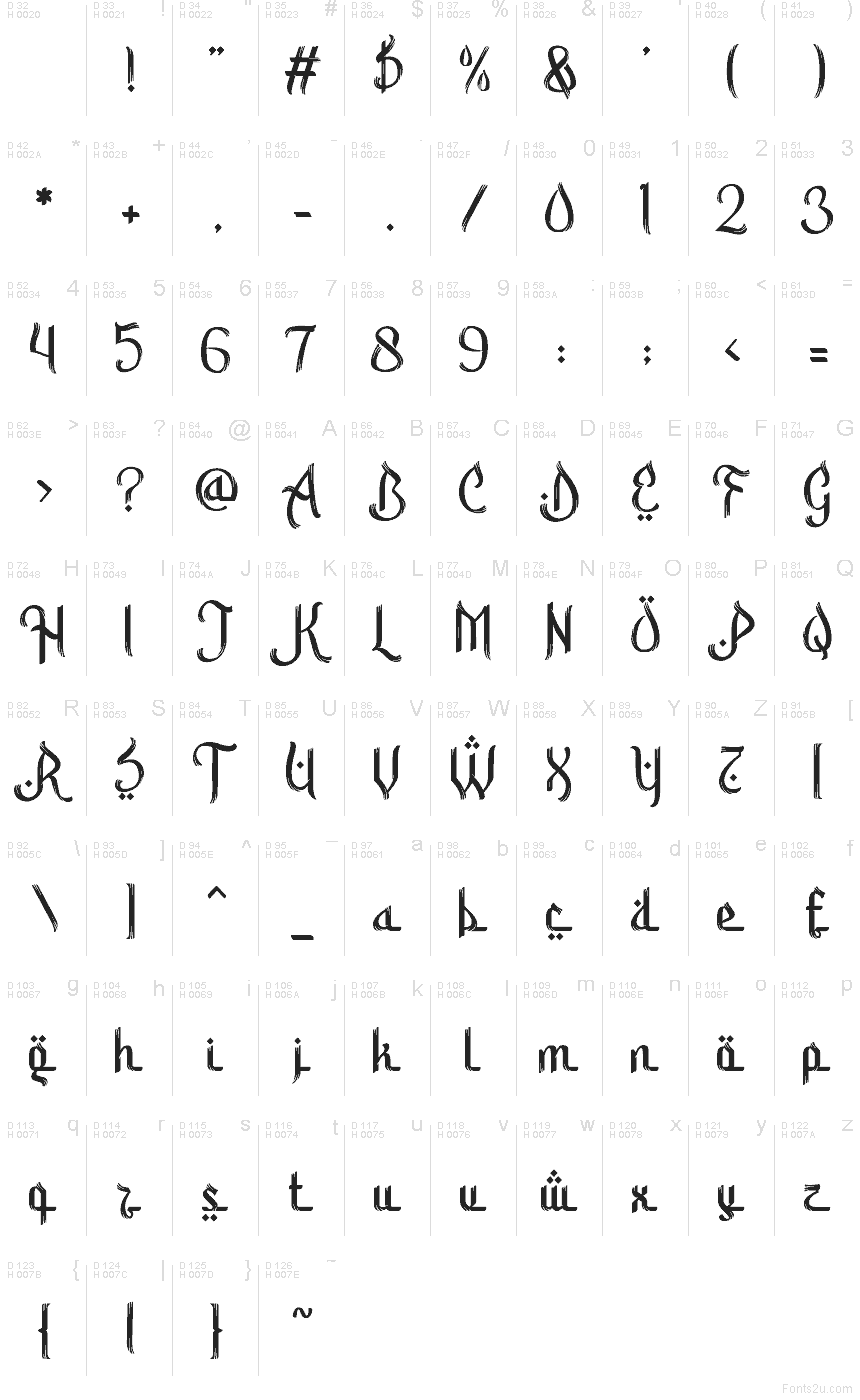
Majidi Mirage One
Majidi Mirage One od štúdia Putracetol Studio je bezplatné display písmo inšpirované arabskou estetikou. Vyniká vysokými čiernymi ťahmi, zahnutými krivkami a jemnými koncami pripomínajúcimi ťah štetcom, ktoré presahujú základnú linku. Opakujúce sa zužovanie dodáva znakom kaligrafický rytmus, zatiaľ čo hranaté vrchné časti a diamantové akcenty udržiavajú dizajn v rámci arabského vizuálneho štýlu namiesto bežnej dekoratívnosti.
Najviac vynikne v brandingu reštaurácií, grafike k ramadánu, na obaloch parfumov, plagátoch podujatí a titulkoch, kde tento kaligrafický rytmus okamžite udáva náladu. Krátke nadpisy a logá obzvlášť ťažia z dlhých spodných ťahov a ostrého vertikálneho zakončenia, ktoré dodávajú jednoduchému textu obradný nádych.